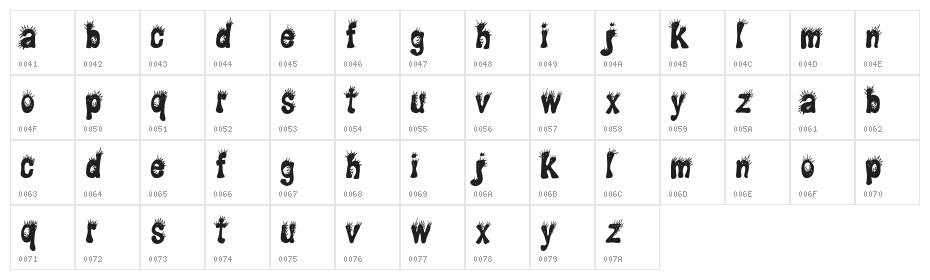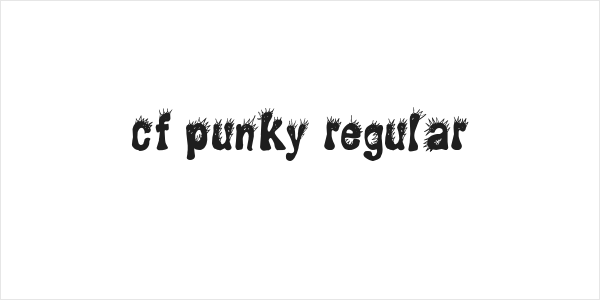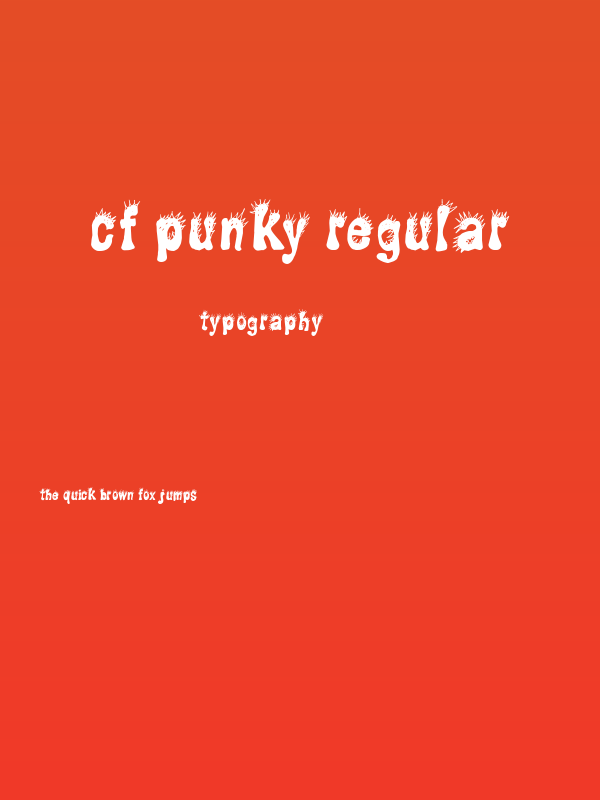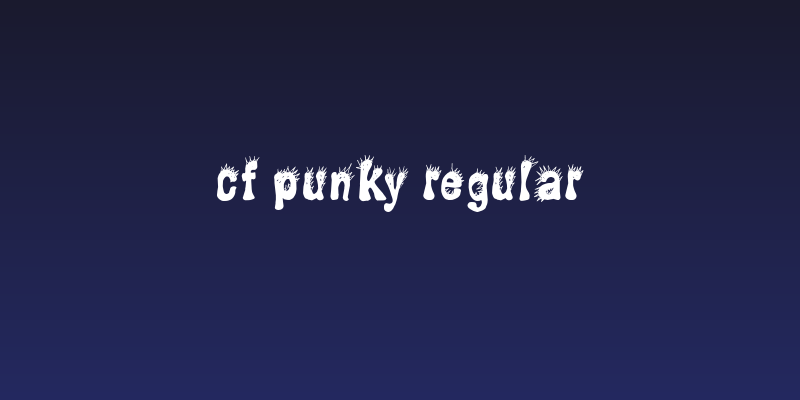
CF Punky Regular Font
| مشاريع مقترحة | Ideal for music album covers, event posters, edgy branding, and creative design projects that require a bold, rebellious look. |